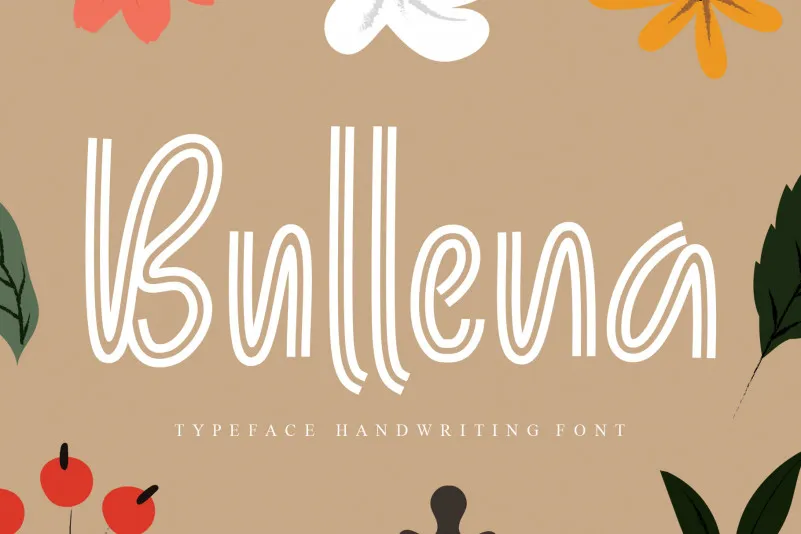
Bullena Display Font
A Bullena Display Font é uma fonte para uso no estilo display que oferece um toque divertido e único. Ideal para qualquer design informais ou artes gratuitas, esta fonte permite que sua criatividade se expanda sem fronteiras. Perfeita para criar um design que seja amigável e interativo, a Bullena Display Font é uma excelente escolha para quem procura dar vida à sua visão pessoal através de um texto único e vibrante. Seja ela o título de seu website, as letras do branding ou até mesmo uma capa personalizada para seus anúncios, esta fonte irá tornar seu trabalho impecável.